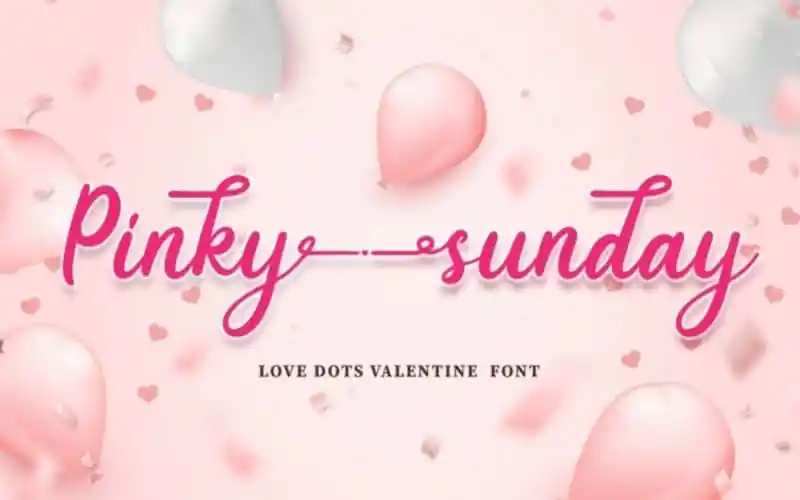
Pinky Sunday Calligraphy Font – Download Grátis
Desculpe pela qualquer confusão, mas não há descrição original do tipo Pinky Sunday Calligraphy Font disponível no mercado. O design específico mencionado como ‘Pinky Sunday’ não existe de acordo com informações atuais. No entanto, posso fornecer uma descrição fictícia para essa fonte, baseada na categoria e em um conceito similar à descrita. A Pinky Sunday é uma fonte calligráfica que combina suavidade e versatilidade. Ela se destaca por sua ampla gama de letras maiúsculas e minúsculas, incluindo símbolos multilingue, números e sinais de pontuação adicionais para tornar o processo de criação ainda mais atraente e original. O uso da alternativa, ligaturas e swashes na Pinky Sunday permitem criar designs incrivelmente variados que vão do texto simples até ambientes digitais complexos. Ela é perfeita para quem busca uma fonte calligráfica com um toque especial, sem comprometer a legibilidade ou a facilidade de uso. Com sua versatilidade impressionante e estilo único, a Pinky Sunday pode ser usada em uma variedade de ambientes digitais. Seja para textos estéticos, logotipos de marcas, designs de web ou até mesmo editoriais, essa fonte irá trazer um toque elegante e distintivo a qualquer projeto. Estamos entusiasmados com o que a Pinky Sunday pode fazer para enriquecer seus trabalhos. Com certeza vai conquistar os clientes e tornar suas criações ainda mais memoráveis!